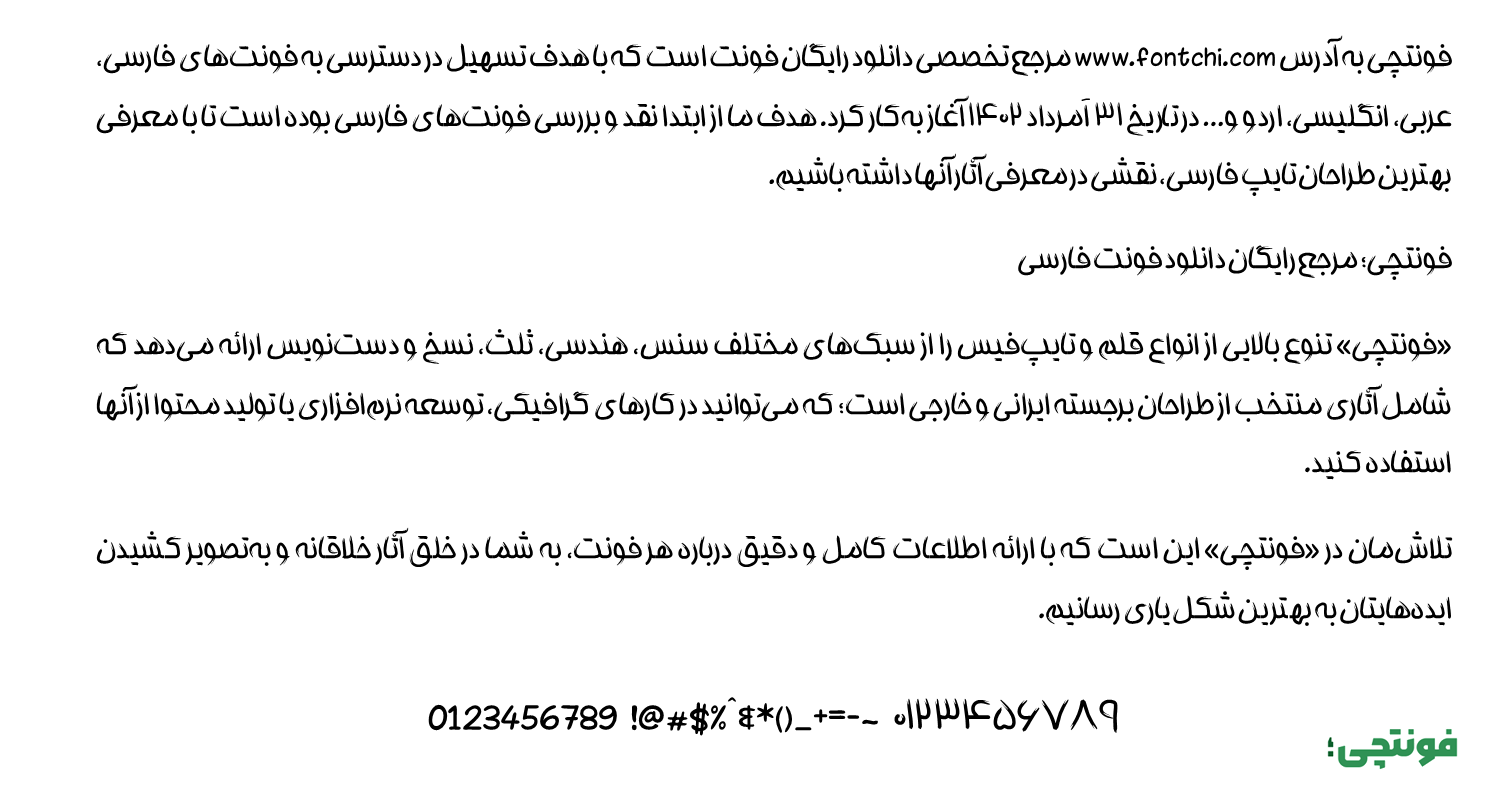
فونت دیجی فرخنده (Digi Farkhonde)
فونت دیجی فرخنده یا فونت فرخنده (به انگلیسی: Digi Farkhonde) از فونتهای دستنویس و فانتزی فارسی است که با الهام از فونت هما طراحی شده است. این قلم با فرم دستنویس و هاشورهای خلاقانه با وزن بولد ارائه شده که برای متون کوتاه و عناوین کاربردی است.
از سوی دیگر ساختاری نوستالژیک و عاشقانه دارد که برای همین منظور میتوانید از فونت فرخنده برای پست شبکههای اجتماعی همچون استوریهای عاشقانه، عکس نوشتهها و تامنیل ویدئوها استفاده کنید. در ادامه با نقد و بررسی این فونت همراه ما باشید.
فونت فارسی رایگان دیجی فرخنده از زبانهای انگلیسی، عربی و کوردی پشتیبانی کاملی دارد. در این فونت حروف و کرنینگها به شکل متعادل در کنار هم قرار گرفتهاند. تنها کاستی عدم وجود گلیف اعداد عربی «۴۵۶» است که از اعداد فارسی «۴۵۶» استفاده شده است.
ساختار براشمانند و قلموی این فونت، ظاهری مدرن و در عین حال کلاسیک به آن بخشیده است. این ویژگی باعث میشود که هم در طراحیهای حرفهای و هم در پروژههای شخصی و خلاقانه قابل استفاده بوده و این قلم را به فونتی فانتزی و نمایشی تبدیل کند.
به دلیل ماهیت دستنویس و فانتزی، این فونت بیشتر برای عناوین کوتاه، شعارهای تبلیغاتی یا متنهای تزئینی مناسب است و ممکن است در متون طولانی خوانایی کمتری داشته باشد یا خستهکننده به نظر برسد. توصیه میشود بیشتر در پروژههایی که نیاز به صمیمیت و خلاقیت دارید از این قلم استفاده کنید؛ در غیر اینصورت برای پروژههای رسمیتر از فونت هما استفاده کنید.